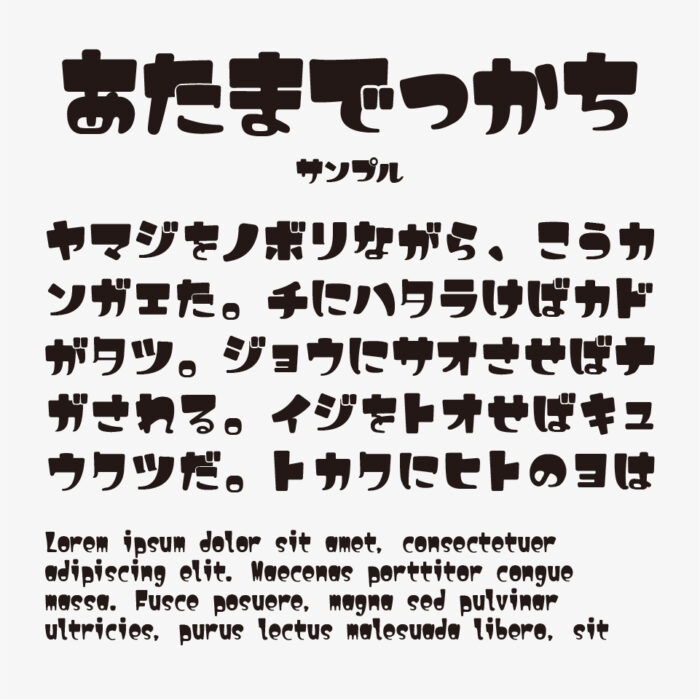
まっつん丸のあたまでっかちフォントは、あたま(上のほう)は大きく、おしり(下のほう)はすぼんだような、ちょっとかわいらしい頭でっかちな少しユニークなフォルムのデザインフォントです。
丸みがあり可愛らしいフォルムと、インパクトがあるので、アイキャッチなどのタイトルとして使ってみるといいかもしれません。
ゲームやアニメなどのタイトルロゴとしても取り入れてみても合いそうです◎
収録文字は、英数字・ひらがな・カタカナ・一部記号、漢字の「丸」の497字の漢字が少なめですが収録しています。